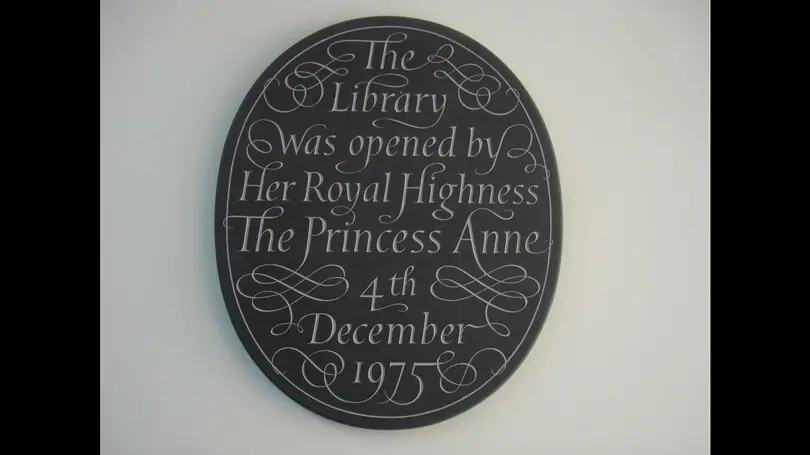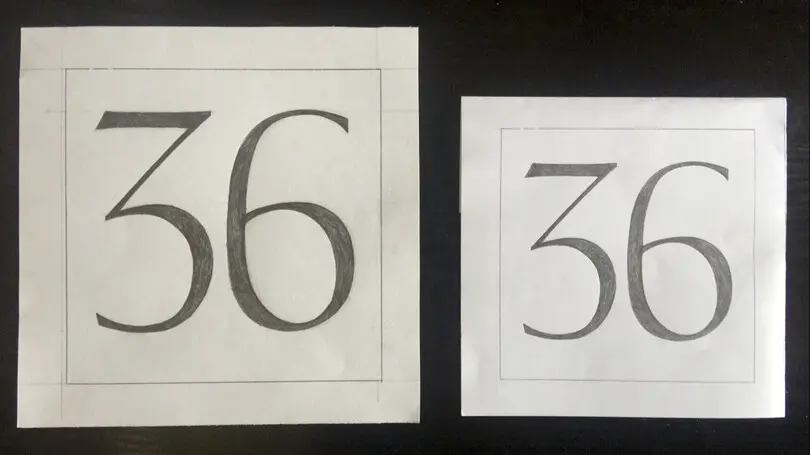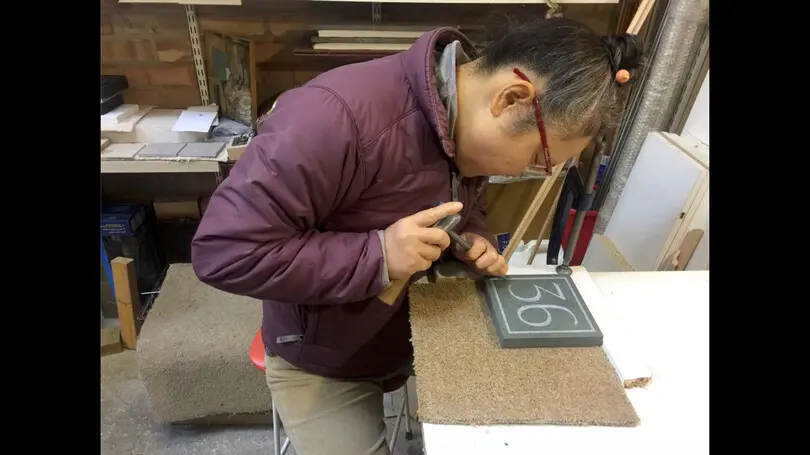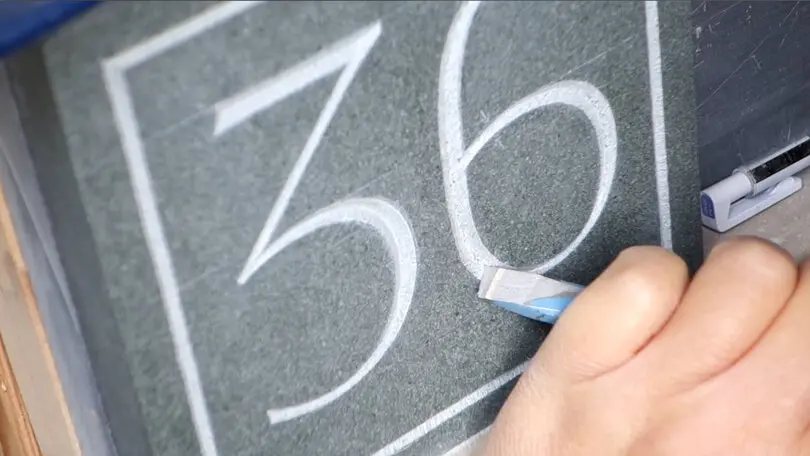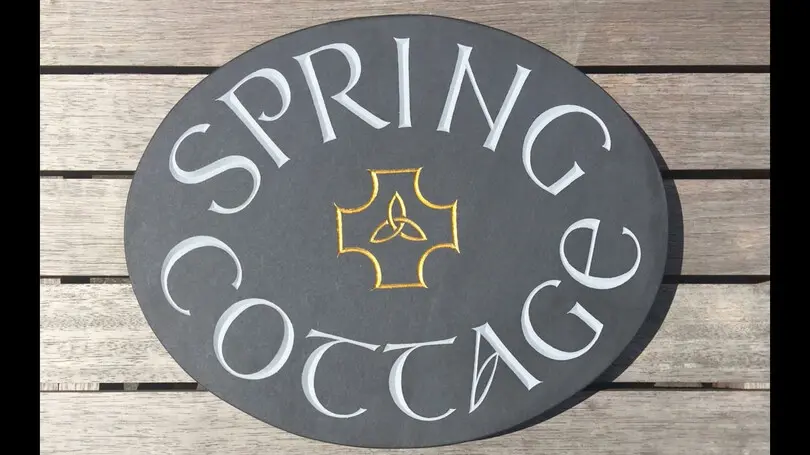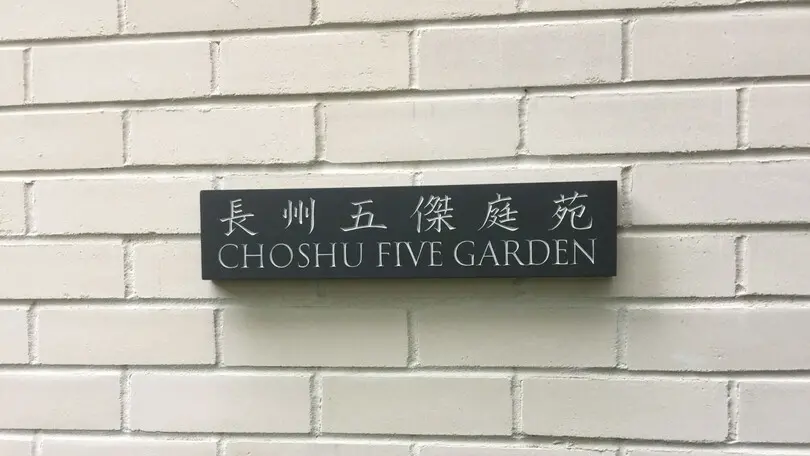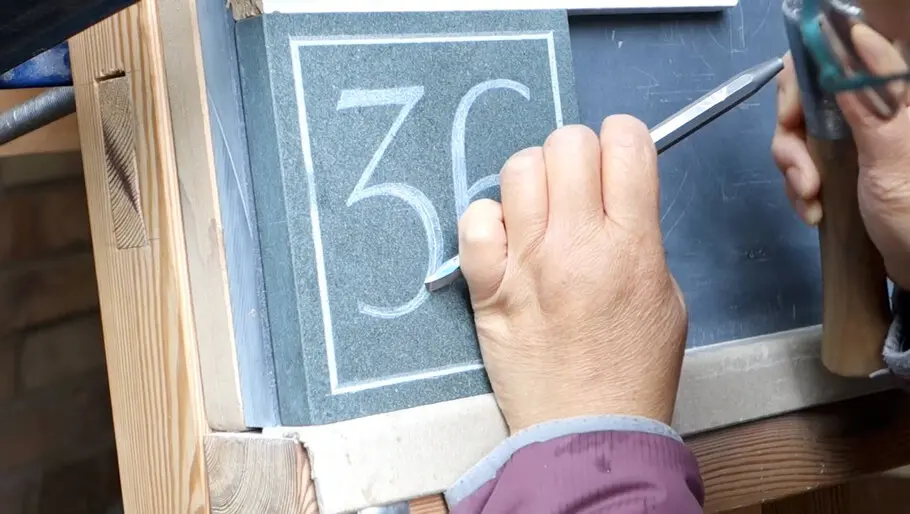
石に文字を手彫りする伝統工芸の技術
レターカッティング
イギリスでレターカッティングの仕事をしているゴードン恵美氏。レターカッティングとは、石に文字を手彫りする伝統工芸の技術です。ゴードン氏は、エリック・ギルのレターカッティングの伝統を受け継ぐCardozo Kindersley Workshopに弟子入りし、2002年から4年半の勤務を経て独立。現在もイギリスでレターカッティングの仕事を続けています。
ゴードン氏が手がけたレターカッティングの仕事3件を紹介します。
ひとつ目の仕事例は、個人宅の玄関に取り付けられたハウスナンバー(住所を示す番号札)。ロジャースさん一家からこの仕事を依頼された際、心がけたのは以下の3点。視認性(認識しやすさ)、石が設置される場所との調和、依頼主との関連性です。
ゴードン氏は、ハウスナンバーが設置される現場に足を運び、依頼主の家族構成や出身地、好みなどを聞きながら、どんな石にどんな文字を彫るのかを考えていきました。
依頼主のロジャースさんは湖水地方に住んでいたことがあるので、そこから採れる緑色の石グリーンスレートを選択。石のサイズは15×15cm、厚さ2cm。建物が建てられたビクトリア時代の書体から、ロジャースさんが好むクラシックな印象の数字を選びたいと考えました。実用的で識別されやすいClarendonが候補に挙がりましたが、現在取り付けられている番号札と似ていることと実用的すぎることから別の書体を検討することに。
そこで、エドワード・ジョンストンが幅広のペンで書いた数字を参考にしながら、「36」の数字を書いてみました。上下に飛び出すオールドスタイル数字ではなく、正方形に収まるようライニング数字を選択。直線を定規で引かず、手書きでわずかにカーブをつけました(3の上と斜めの線の部分)。3と6の線幅が揃うよう、ティッカーという道具で確認します。下書きを玄関に置いてみて、文字の大きさを20%小さくし、数字のまわりに囲み線をつけました。これでデザインが完成です。
次に、石板が欠けないよう、やすりをかけて角を落とします。数字をチャコペーパーで石の表面に写し、水彩鉛筆で下書きをして、ロジャースさんに確認してもらいます。石の裏面に金具を取り付けるための長方形の凹みを彫ってから、表面を彫り始めます。通常は石板を立てて彫りますが、今回のように囲み線があるときは平らに置いて彫ります。
最初に、数字のまわりの囲み罫線をVカットで彫っていきます。Vカットとは、Vの字に深く凹む彫り方で、古代ローマ時代に確立され、トラヤヌス帝の碑文にも使われているそうです。それから、数字の中央にVカットの中心線を入れていきます。これはチョップと呼ばれる彫り方で、線幅が広いほどVカットの傾斜が深くなります。Vカットの左側と右側の角度を揃えるようにして彫り、Vの一番深いところが彫れたら、側面をきれいに整えていきます。
彫り終わったら、石の粉を払い、色づけします。彫られた箇所とそのまわりを白く塗り、石板の表面にヤスリをかけると、「36」の文字が浮かび上がりました。これで完成です。
2つ目の事例は、アンジェラさん宅のハウスサイン。「SPRING COTTAGE」とアンシャル体で書かれ、真ん中の十字架にギルディングと呼ばれる手法で金箔が貼られています。イギリスでは、日本のように名字を入れた表札ではなく、家の名前を書いた表札を飾ります。
3つ目の事例は、ケンブリッジにある「The Kaetsu Educational & Cultural Centre」の日本庭園「長州五傑庭苑 CHOSHU FIVE GARDEN」。漢字の部分は下田恵子氏の楷書、アルファベットはゴードン氏のローマンキャピタルで書かれています。
「(石に文字を彫る時に)フォントやタイプフェイスは使わないのか?」と聞かれることがありますが、フォントをそのまま使うのは無理があります。レターカッティングでは、文字をかなり大きく使いますし、石の性質上、フォントの細いラインが出せなかったり、設置する場所によって文字の太さを調整したりしなければならないからです。
フォントは誰かがつくったものであって、自分がつくったものではありません。文字を彫る時にはその文字のイメージがしっかりと頭の中に入っていないと、きれいには彫れないのです。
⽂字を書くときにどんな⼯夫をしていますか?
自分にとって心地よい文字を探すようにしています。ベルリンのアーカイブセンターでアドリアン・フルティガーのUniversの原画を見た時、背筋が凍りました。頭の中ではUniversは機械的な文字だと思っていましたが、直線にちょっとだけカーブがかかっていて、この線は神様しか出せないと思ったんです。自分で本物を見て、自分がどういうところに反応しているかを大事にしながら文字を書くようにしています。原画に近いものを見て、目をこやしながら自分の仕事に反映させていくのです。
どこを見てデザインの特徴をつかんでいますか?
セリフ、xハイトに対しての線の太さです。エドワード・ジョンストンが自分なりに調べて分析した結果を記した書籍『Lessons in Formal Writing』を参考にしています。
合字を効果的に活かせるコツをうかがいたいです。一方で、合字を使わない方がよいシーンもあればおうかがいしたいです。
また、欧文合字は日本人から見るとあまり見慣れないため、可読性が落ちることもあると思うのですが、英語圏の方はみな問題なく読めるものなのでしょうか?
まず、合字についてです。私個人の意見としては、基本的には合字は利用せずに、できれば他の方法で問題を解決した方がよいと思っています。なぜなら、合字が必要とされる理由をまず考えていただきたいと思います。合字を用いる目的は主にスペーシングの調整と複数の行長を揃える(全体の統一感)ためなのですが、合字がどんな場面で使われるのかを考慮するのも大変重要なのではないかと思います。
例えば、本などに印刷されている文章の書体に合字が多く入りすぎている場合には、読みやすく文章を組んであるとは言えないでしょう。上手に文章組をする人であれば、合字を入れる以前に様々な調整をして文章が置かれる紙面の上にきれいに入り、なおかつ読みやすいように文章を組むと思います。
次に、石に彫る文章に合字を使う場合を考えてみましょう。石は紙とは比べられないほど高価なので、長い文章があるからと言って簡単には字を彫る石の大きさを変えることはできません。そういった高価な石の面に長文を彫る場合は、文字自体を小さくしたり、文章のまわりの余白(マージン)を少なくしたり、文字間のスペースも極力狭める必要も出てきます。このような調整をしてもまだ問題が残る場合、合字を使うことは問題を解決する一手段と言えます。合字はあくまでも全体のデザイン、レイアウトを整えるために使われた場合に効果的と言えるのではないでしょうか。